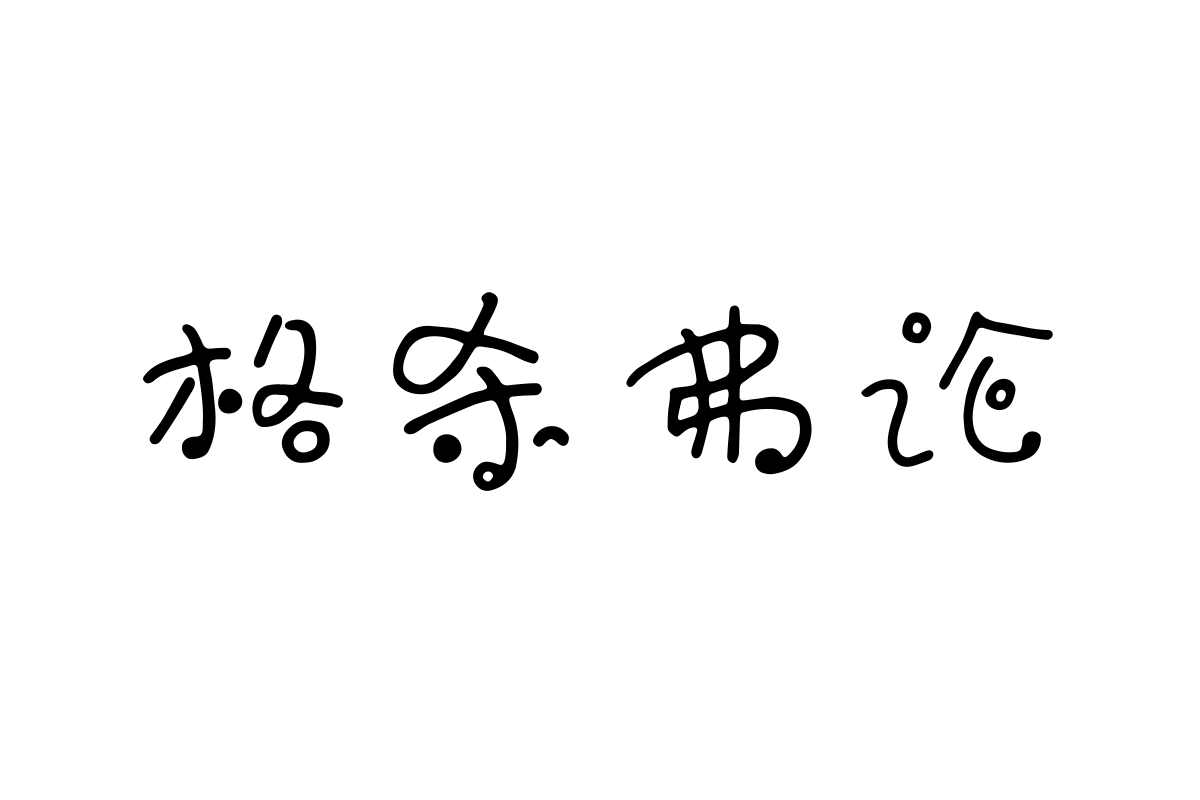
上首趣泡手写体是一款具有独特风格的中文字体,由上首科技设计并开发。这款字体以其独特的笔触和风格而闻名,给人一种轻松、随意的感觉。
上首趣泡手写体采用了一种类似于手写的笔触,使得文字看起来更加自然和生动。它的笔画流畅,线条柔和,给人一种亲切感。同时,这款字体也具有一定的艺术感,适合用于需要强调个性和创意的场合。
在字形结构方面,上首趣泡手写体保持了中文书写的基本特点,同时也融入了一些现代元素。这使得它在保持传统美感的同时,也能够满足现代人的审美需求。无论是用于广告、设计还是个人使用,上首趣泡手写体都能展现出其独特的魅力。